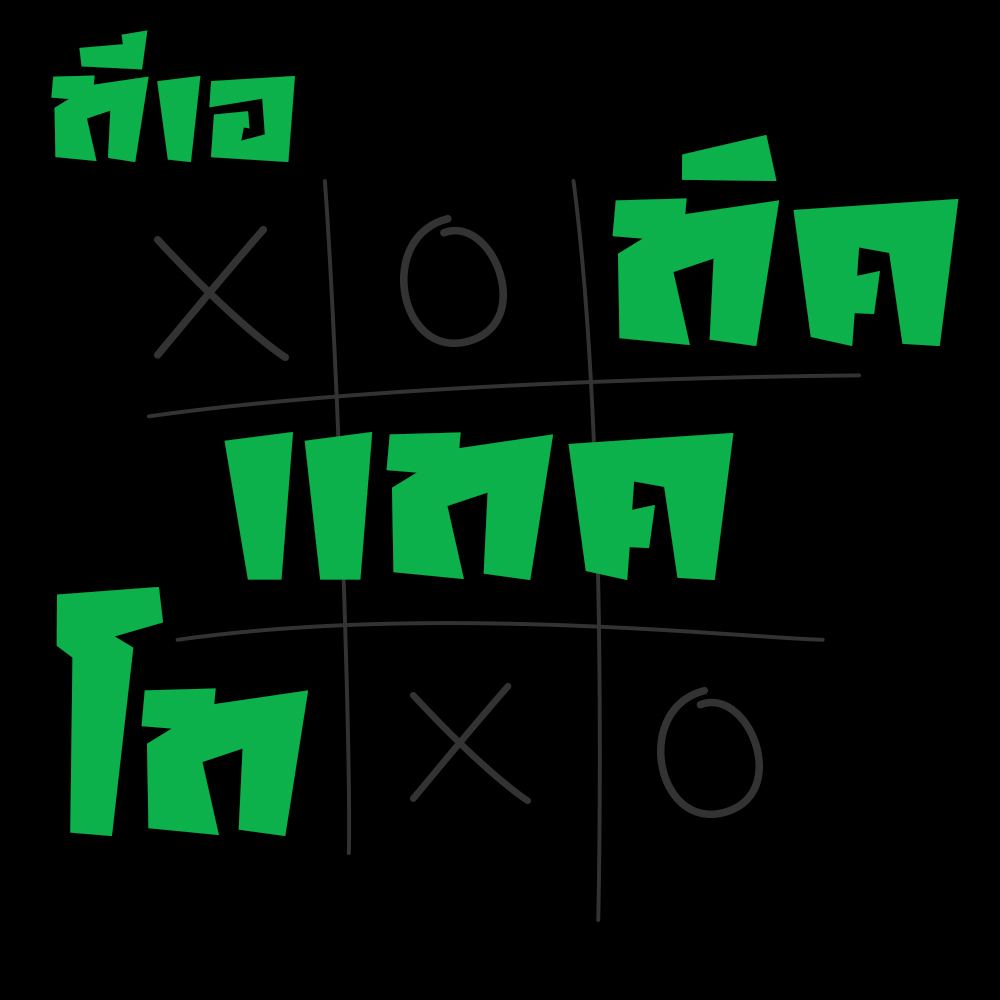
ทีเอ ทิคแทคโท ฟอนต์ / TA TicTacTo
ฟอนต์ ทีเอ ทิคแทคโท (TA TicTacTo)
เป็นฟอนต์ที่อยากทำฟอนต์ตัวหนาๆ แท่งๆ โดยใช้ภาพจำมาจากหนังสือการ์ตูน
เวลามีฉากแอคชั่น หรือเสียงดัง จะใช้ตัวหนังสือแท่งๆ เหลี่ยมๆ แทนเสียง
แล้วก็ลองขึ้นแบบใน Adobe Illustrator ก็ได้ออกมาประมาณนี้
ฟอนต์ตัวเต็มมี 4 น้ำหนัก 8 สไตล์
ฟอนต์ที่นำมาแจกในเว็บนี้เป็นฟอนต์ ทีเอ ทิคแทคโท ตัวหนา